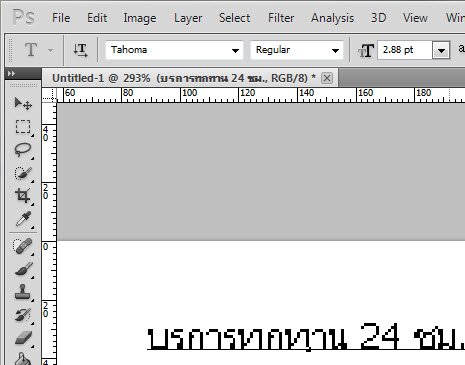
ฟอนต์นี้ฟอนต์อะไรครับ!
มีคนบอกtahoma ขนาดเล็กผมลองแล้วไม่ใช่ครับ! :12:
มันจะใช่ก็ต่อเมื่อคุณใช้ขนาดที่ถูกต้องครับ เพราะบางฟอนต์เมื่อเปลี่ยนขนาด อาจมีรูปร่างในการแสดงผลที่แตกต่างกันนิดหน่อยครับ
ต้องดูให้ดี
แต่ผมใช้แล้วสระลอยอะครับแก้ยังไง
ใช้ ASK Square Free ครับ